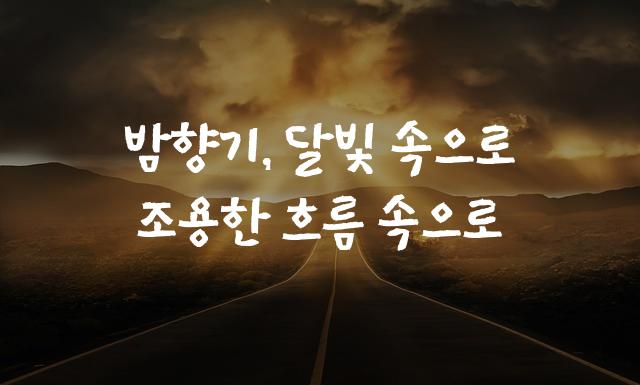
한컴 울주 천전리 각석체는 울주문화재단에서 제작한 기본 고딕 스타일의 폰트입니다. 세련되고 현대적인 디자인이 특징으로, 전통과 모던함을 조화롭게 표현합니다.
한컴 울주 천전리 각석체은(는)
기본 고딕, 감성적인, 부드러움 계열의 생김새를 가지고 있으며
출판 디자인, 출판물 제목 등에서 자주 활용되며, 효과적인 메시지 전달에 적합합니다.
이 폰트는 출판/미디어, 건축/인테리어 분야에 잘 어울리며,
전통적, 클래식한 느낌을 담고 있는 것이 특징입니다.